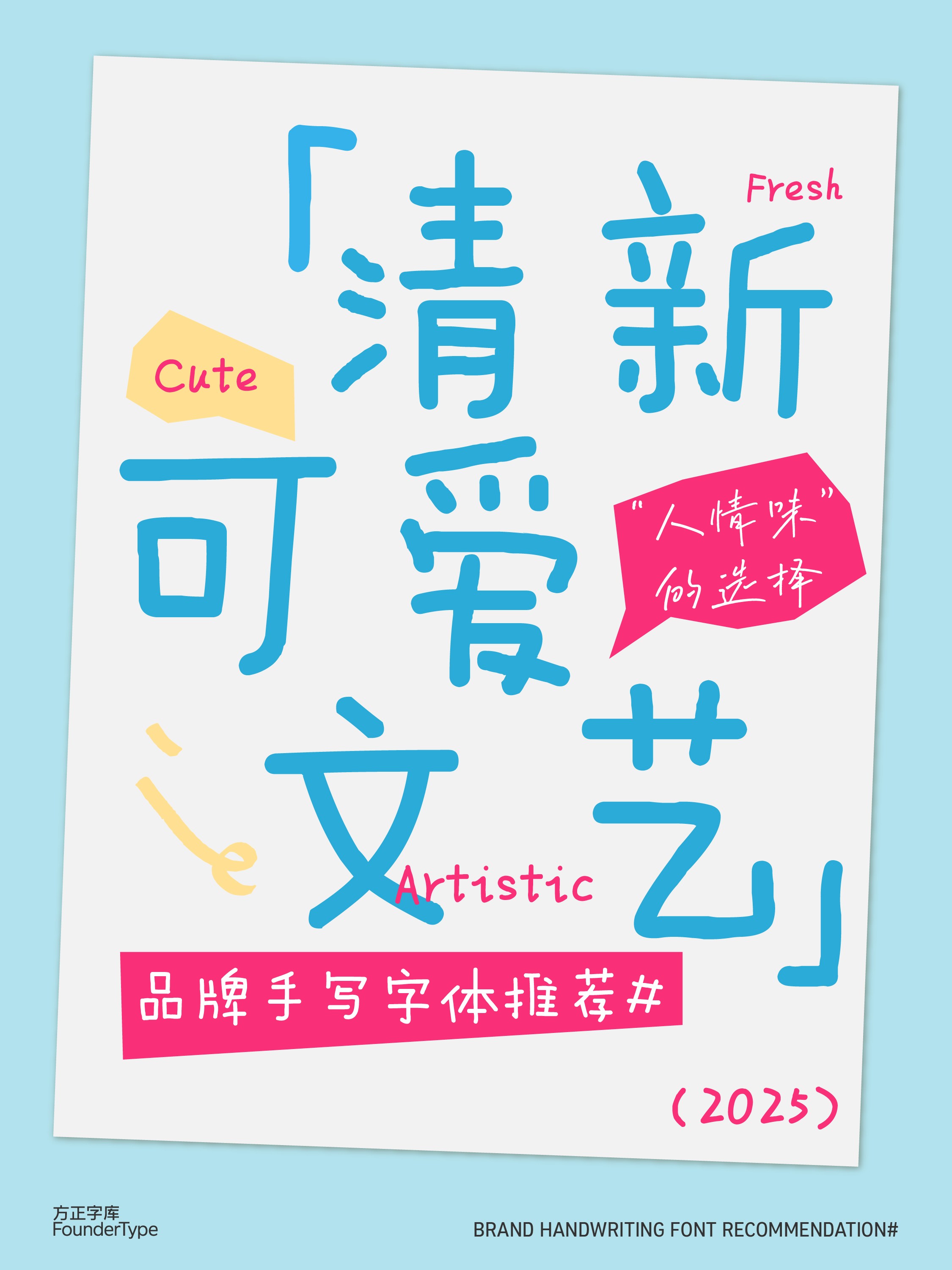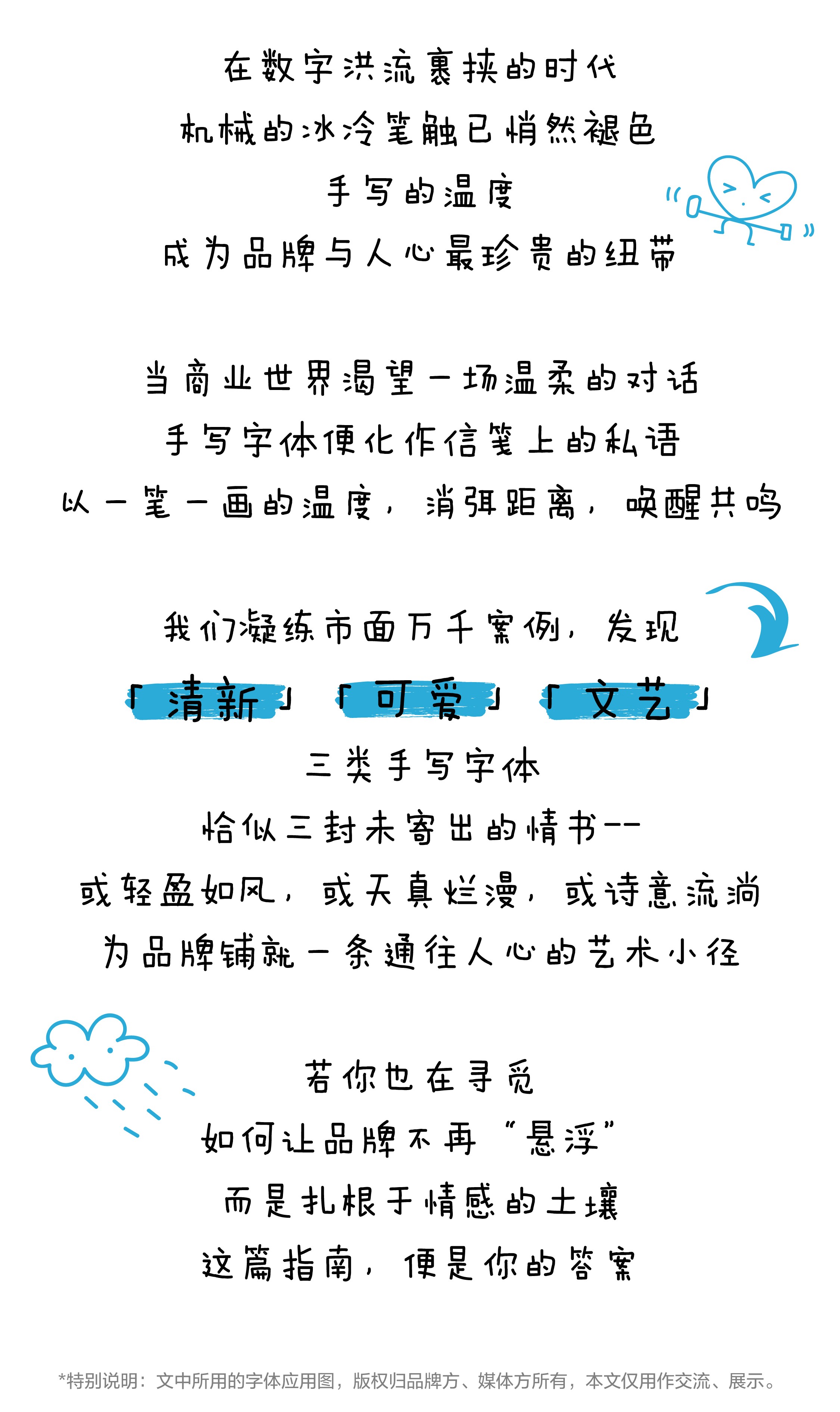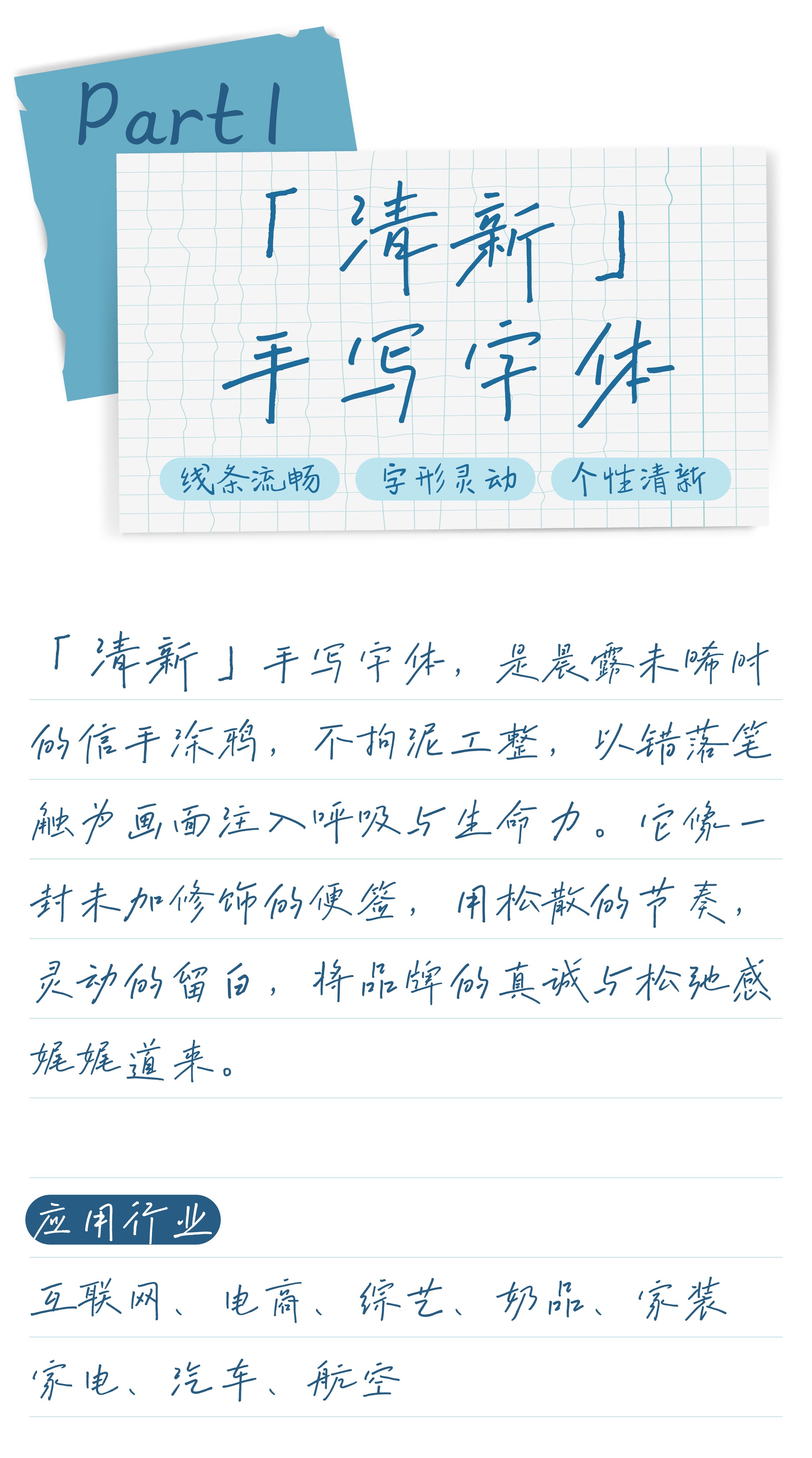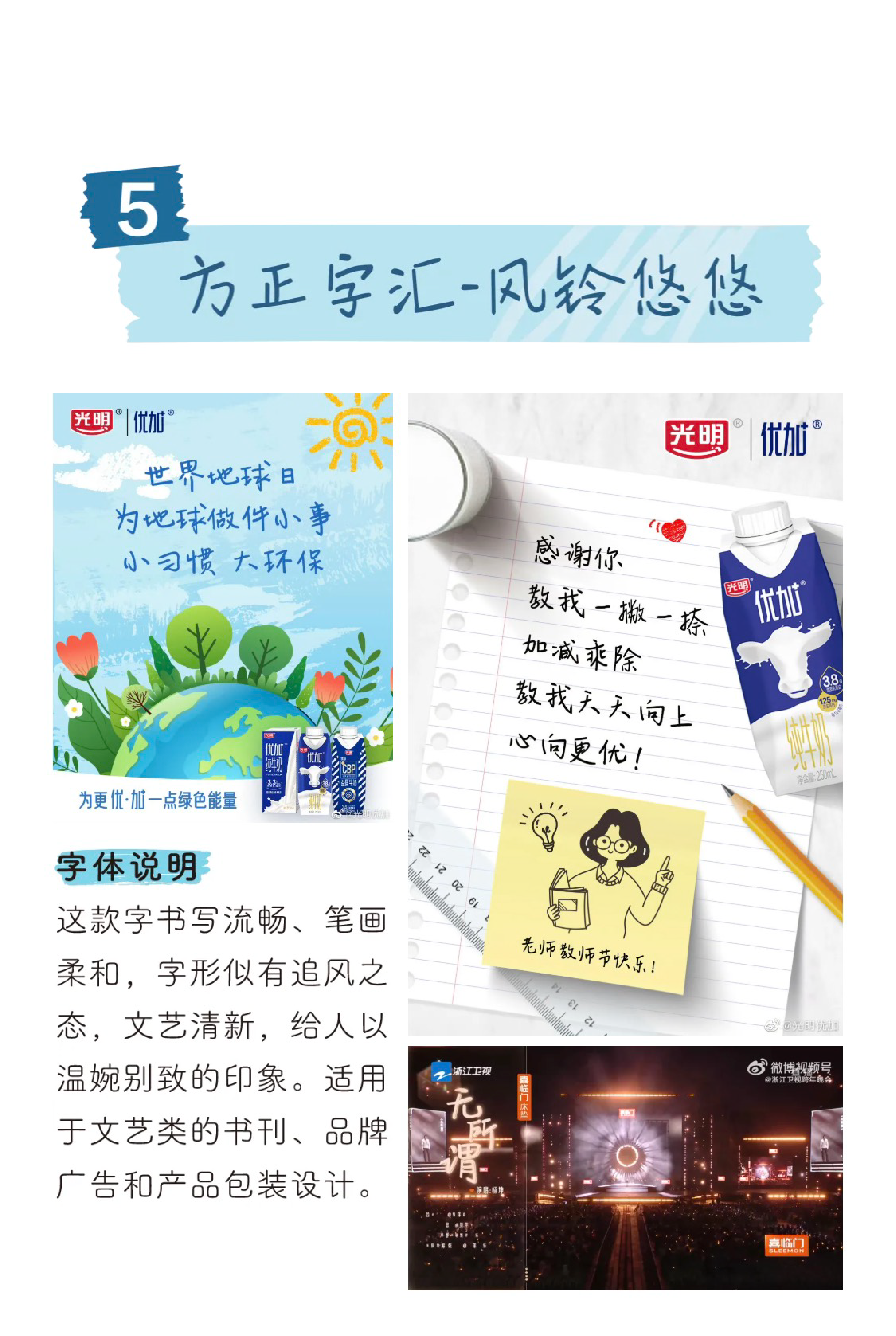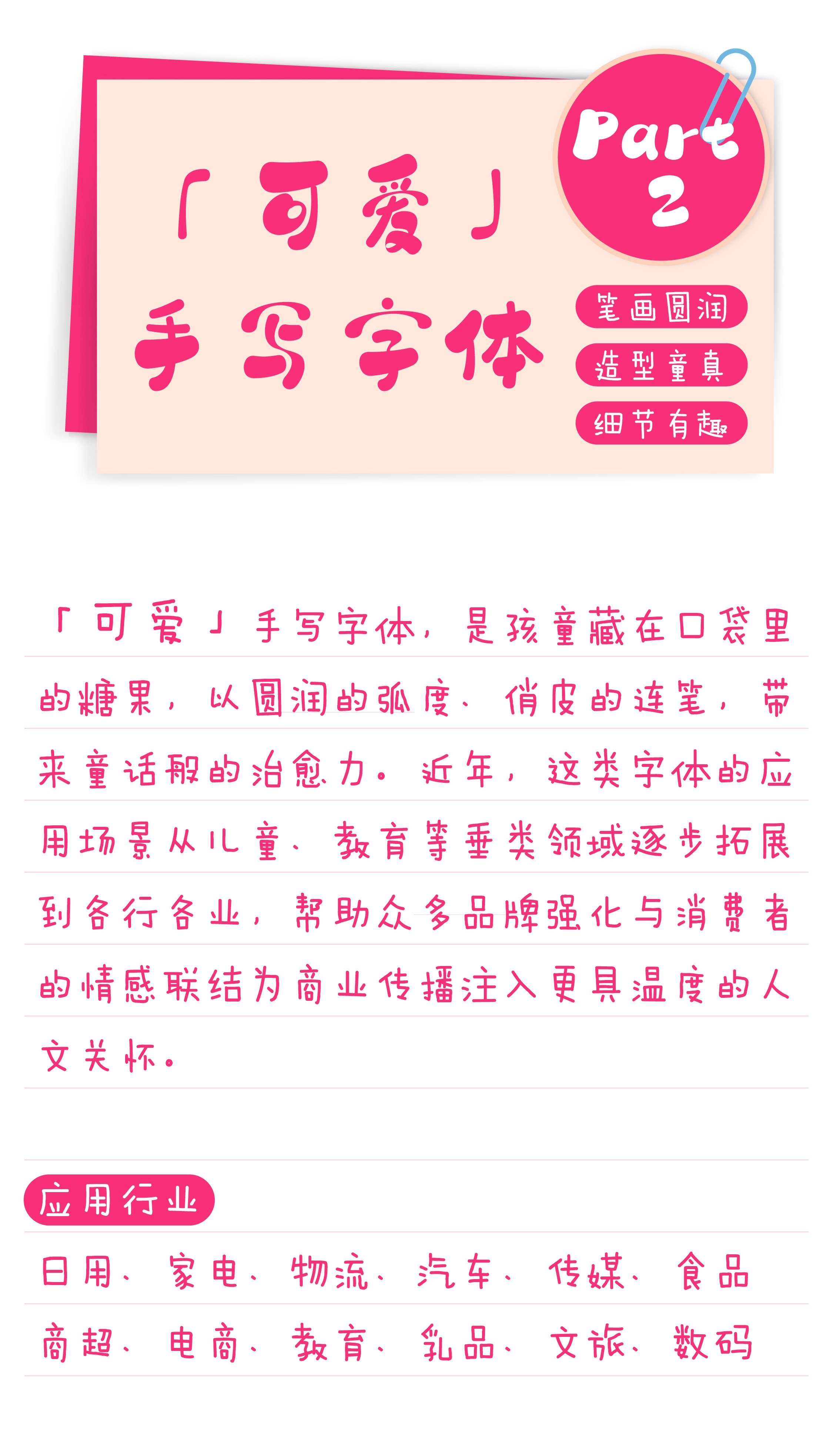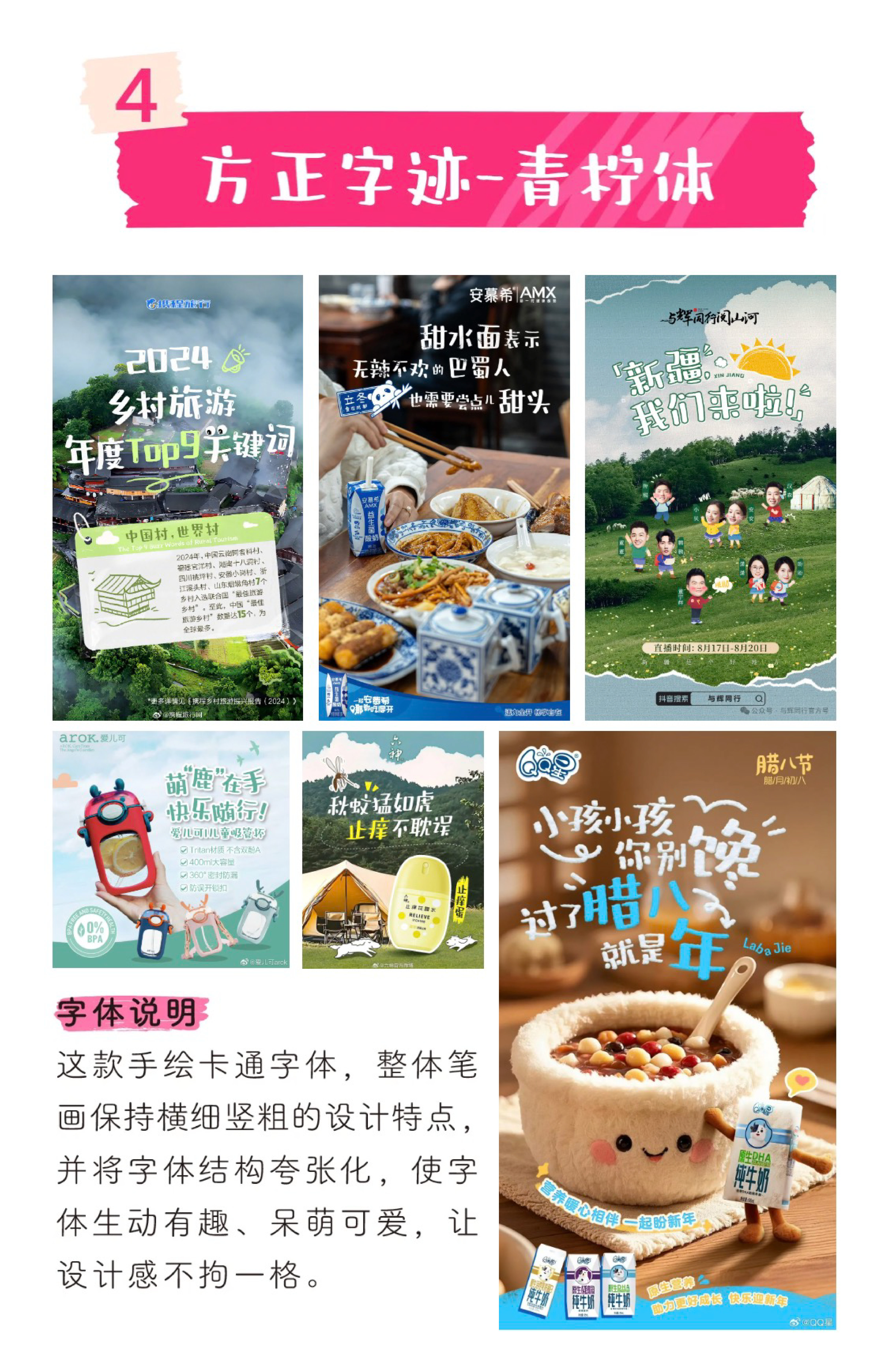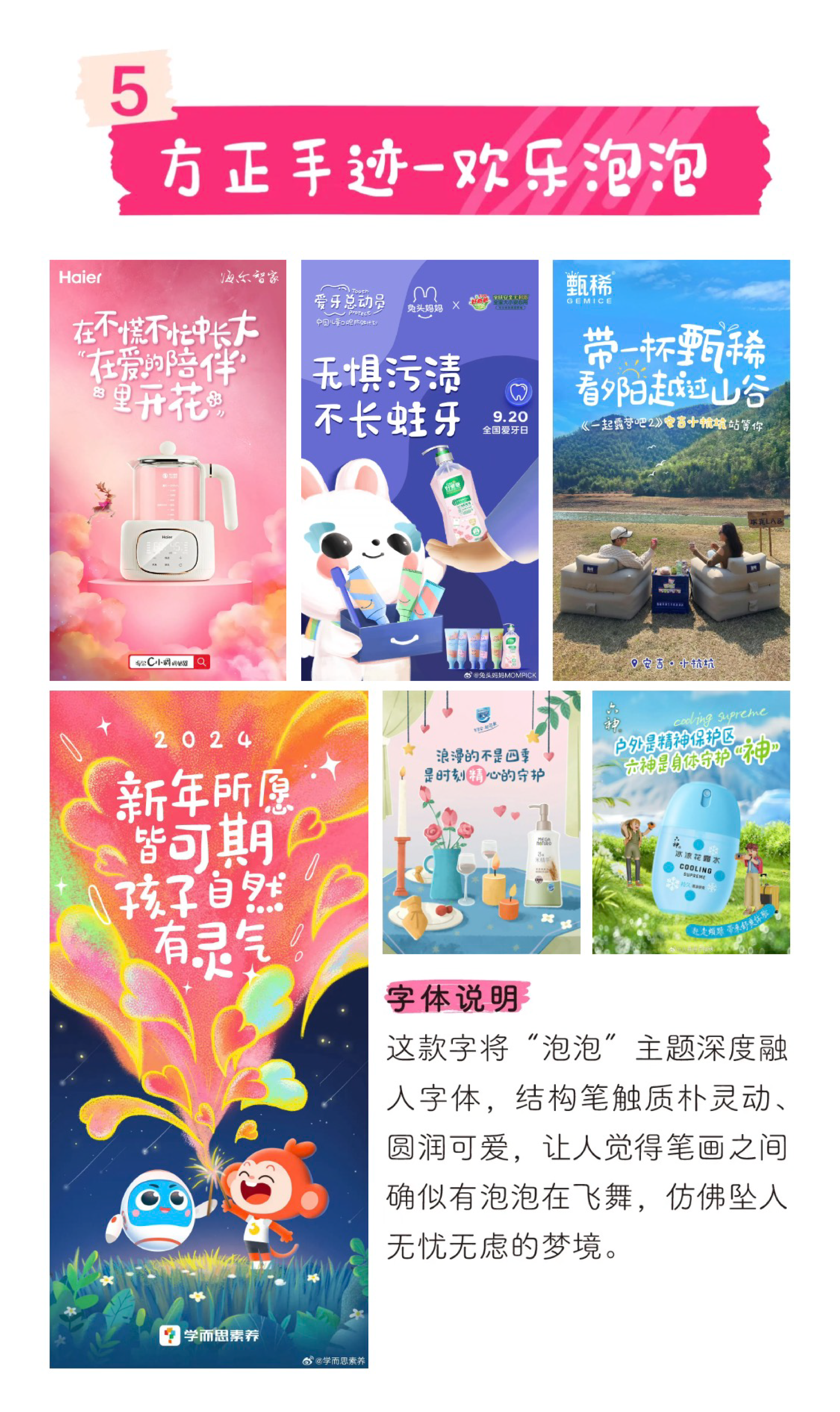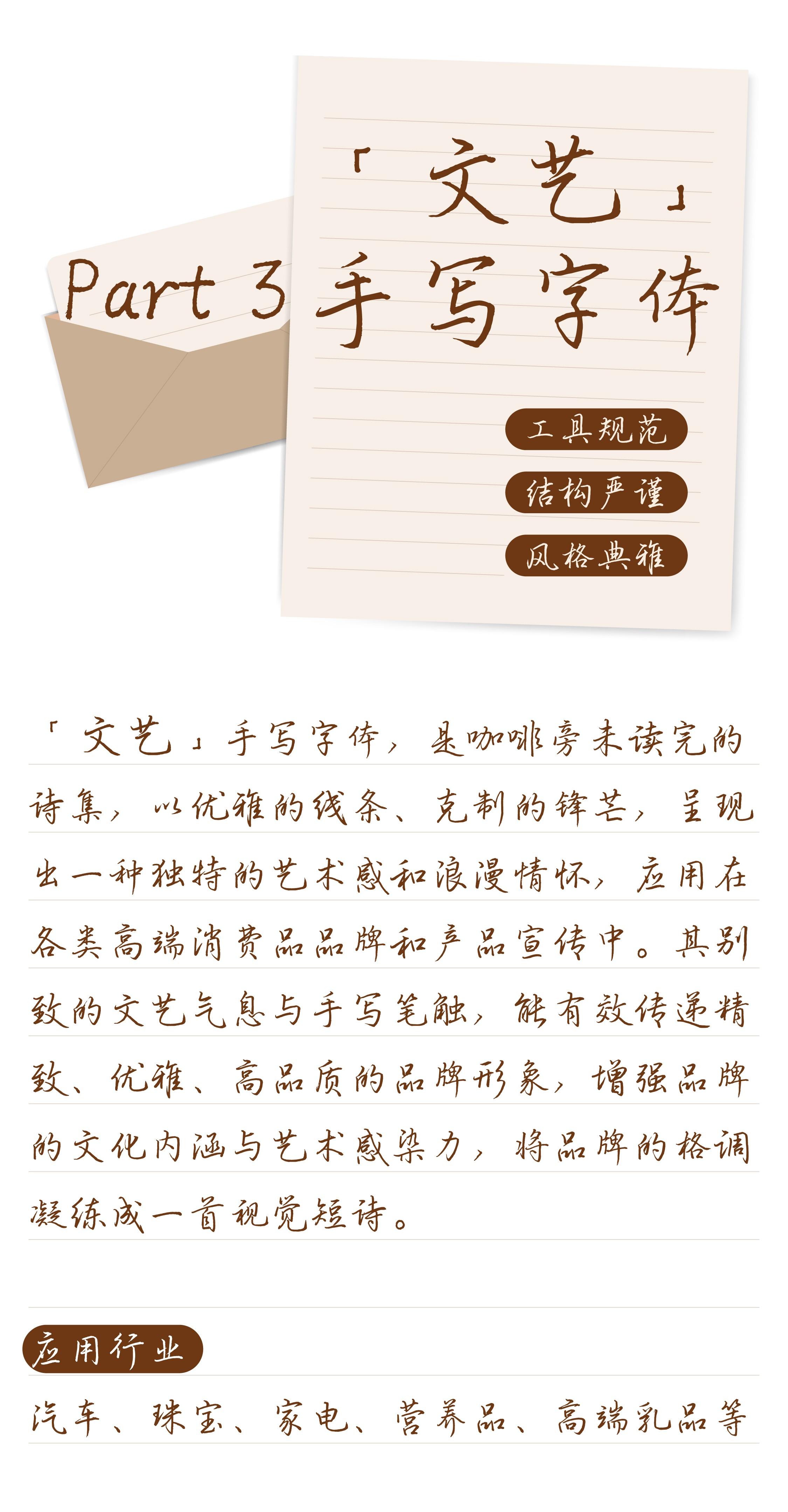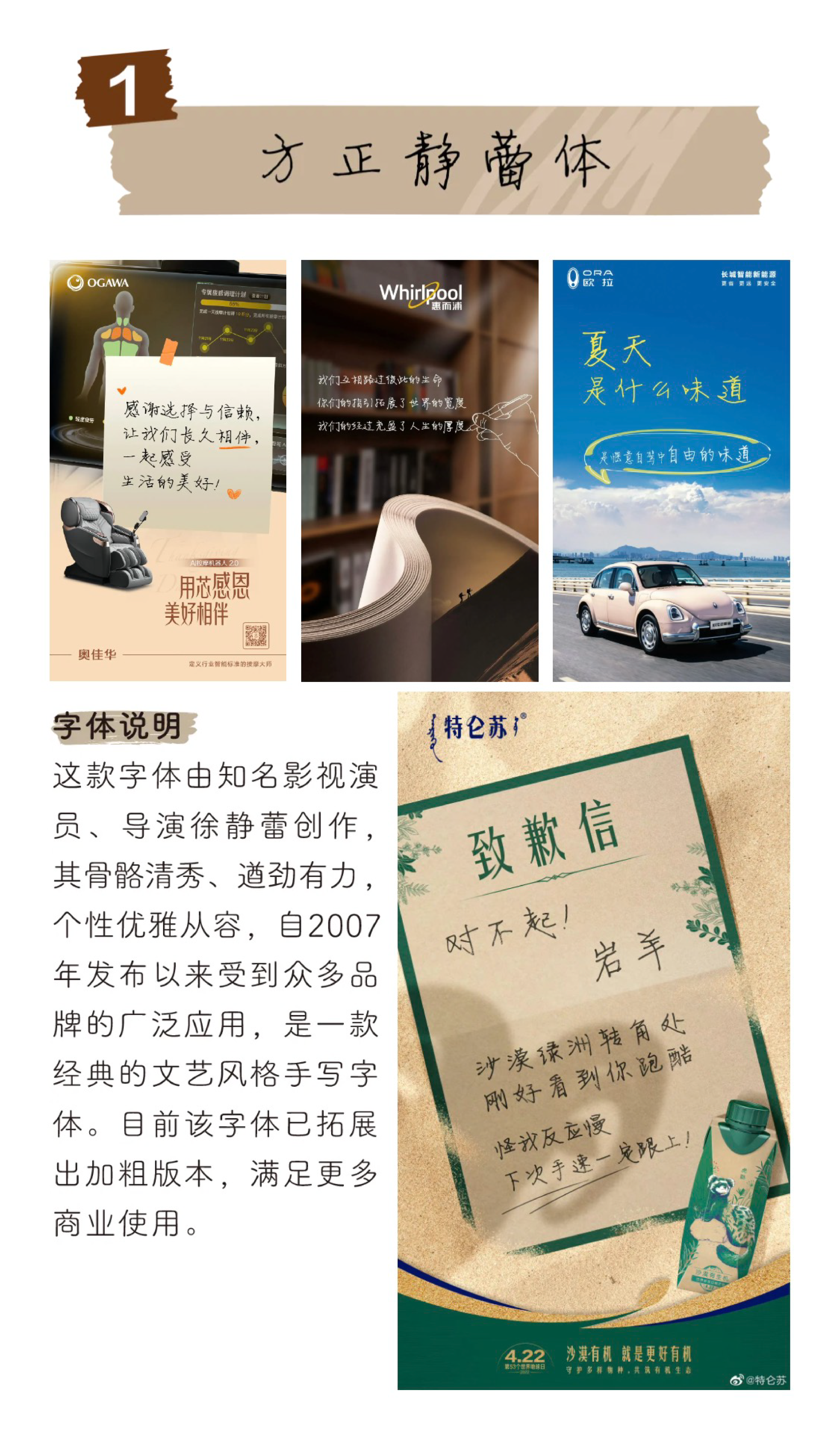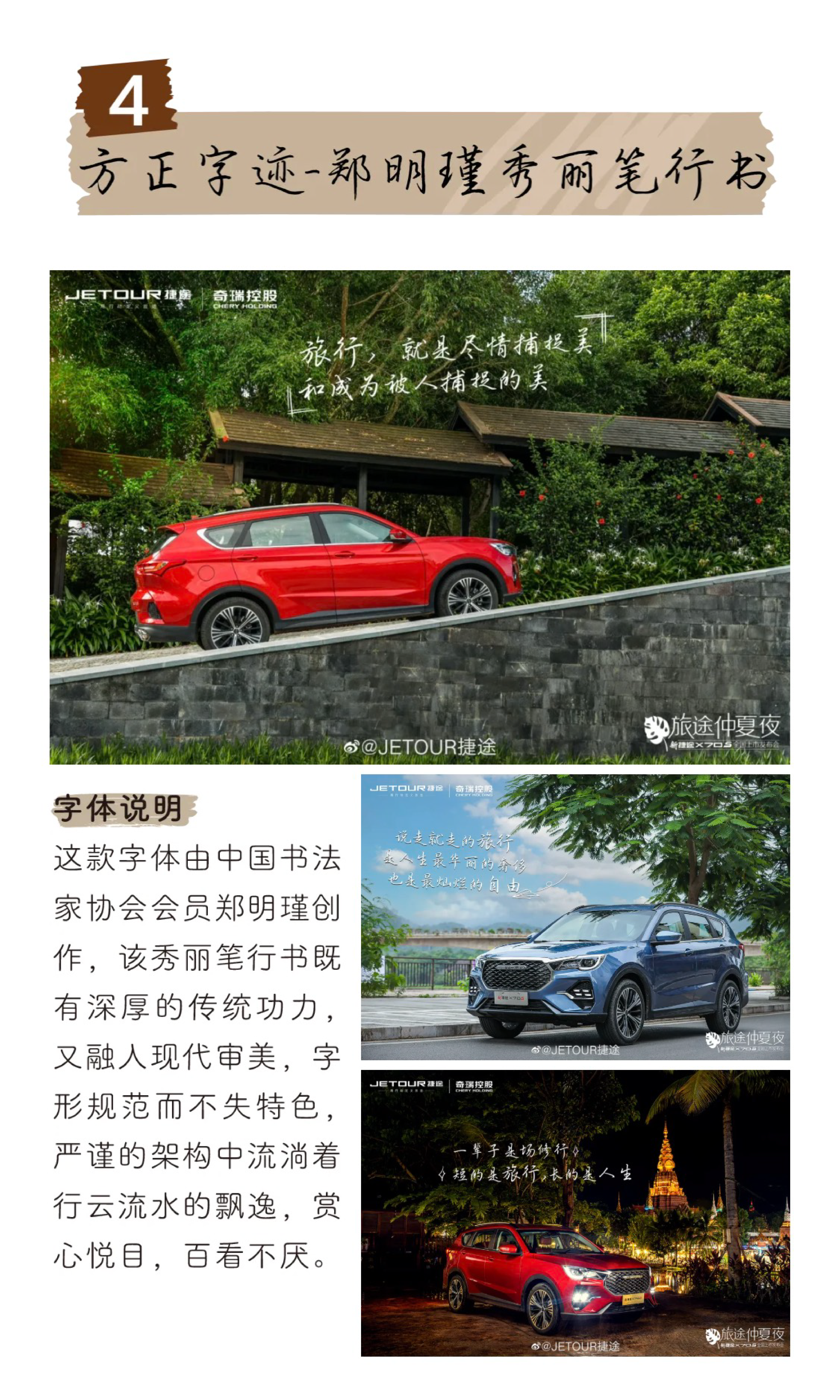三类手写字体推荐,为品牌注入“纸短情长”的温度
在数字洪流裹挟的时代,机械的冰冷笔触已悄然褪色, 手写的温度,成为品牌与人心最珍贵的纽带。 当商业世界渴望一场温柔的对话, 手写字体便化作信笺上的私语, 以一笔一画的温度,消弭距离,唤醒共鸣。 我们凝练市面万千案例, 发现「清新」「可爱」「文艺」三类手写字体 恰似三封未寄出的情书-- 或轻盈如风,或天真烂漫,或诗意流淌, 为品牌铺就一条通往人心的艺术小径。 若你也在寻觅, 如何让品牌不再“悬浮”,而是扎根于情感的土壤? 这篇指南,便是你的答案。